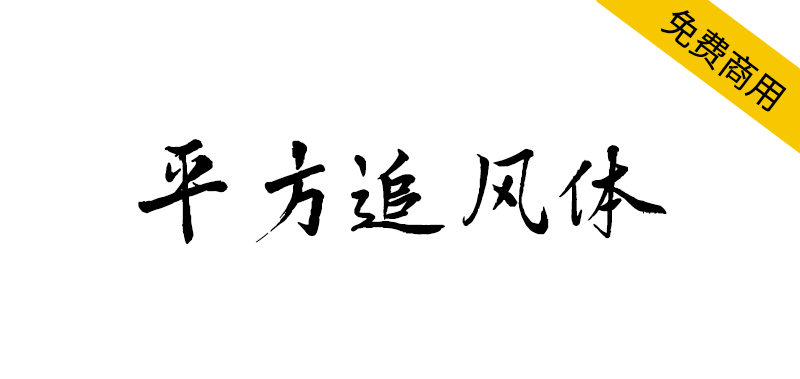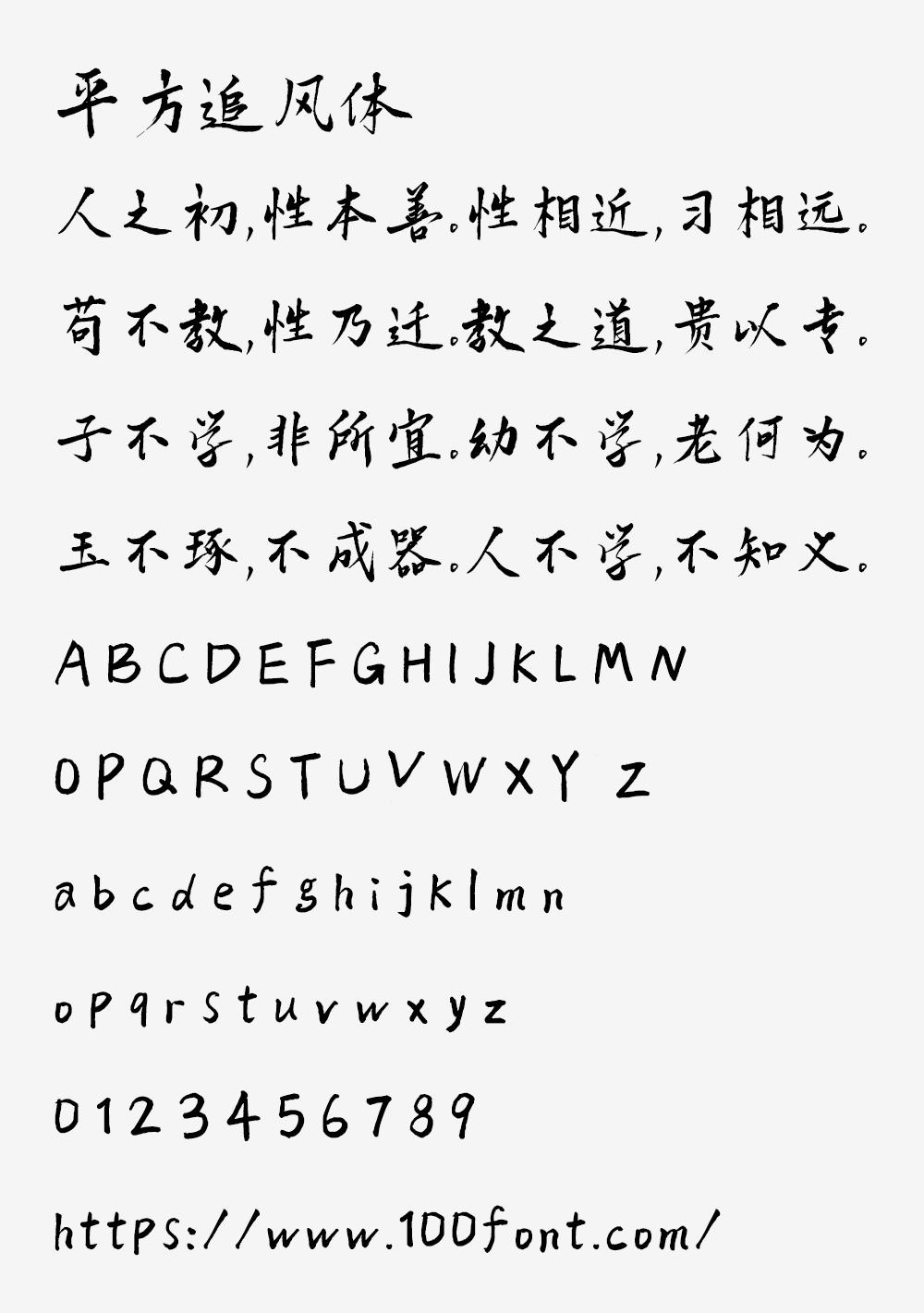
【平方追风体】一款具有古典韵味的毛笔手写字体
当现代设计遇上千年书法,会碰撞出怎样的火花?这款免费商用的平方追风体给出了惊艳答案。它以传统毛笔笔触为魂,字形恢弘大气,艺术表现力十足,让每个汉字都跃动着古典韵律。无论是品牌设计、广告创意还是艺术创作,只需一键应用,就能为作品注入独特的文化底蕴与视觉张力。无需付费,即刻解锁设计师私藏的字库瑰宝。
【平方追风体】一款具有古典韵味的毛笔手写字体
平方追风体是一款具有古典韵味的毛笔手写字体,其笔触设计饱含传统书法精髓,字形恢弘大气且富有艺术表现力。这款字体凭借鲜明的古典美学特征和出色的艺术感染力,在字体设计领域独树一帜,深受设计师青睐。无论是商业设计项目还是艺术创作,平方追风体都能为作品注入独特的文化韵味和视觉张力。